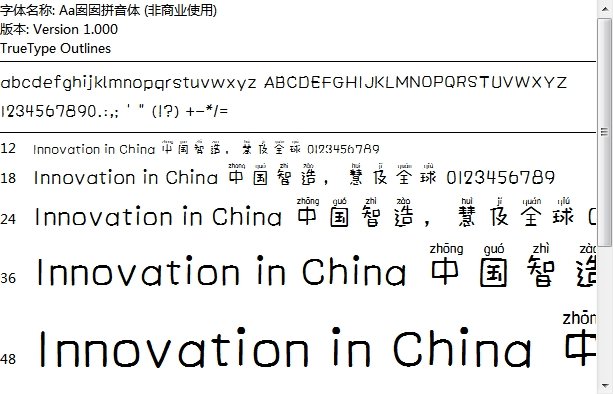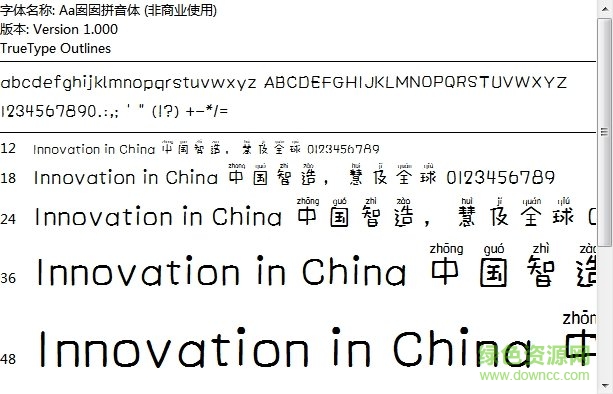
囡囡拼音體是aa字體官方推出的一款可愛拼音字體,字形可愛清秀,讓你感受吳儂軟語(yǔ)的溫柔之美,讓你在第一時(shí)間感受舒適的美感,來綠色資源網(wǎng)試試吧!
囡囡拼音體有著溫潤(rùn)柔和的藝術(shù)美感,因取材字江南地區(qū)獨(dú)有的鄉(xiāng)音,文字間更是充滿了生動(dòng)和嬌柔的女孩兒氣息,清香芬芳,十分宜人,用作兒童文字、情感表述等內(nèi)容的修飾再合適不過了!
囡囡,是吳語(yǔ)區(qū)、粵語(yǔ)區(qū)等方言區(qū)對(duì)女孩的昵稱,亦有寶貝的意思。囡從造字詞義上看,女外有圍,意為閨,女入閨中,可意會(huì)為閨中少女,未聞世的小女孩,這也是古意囡囡稱呼小女孩。